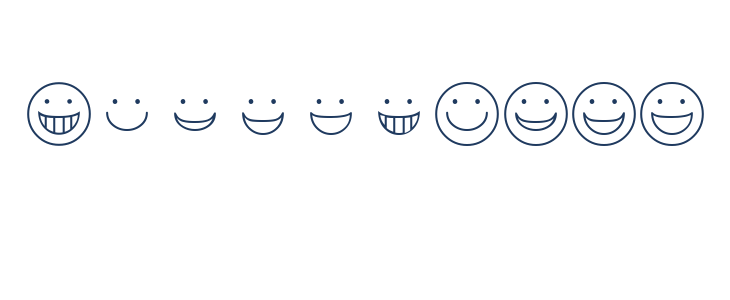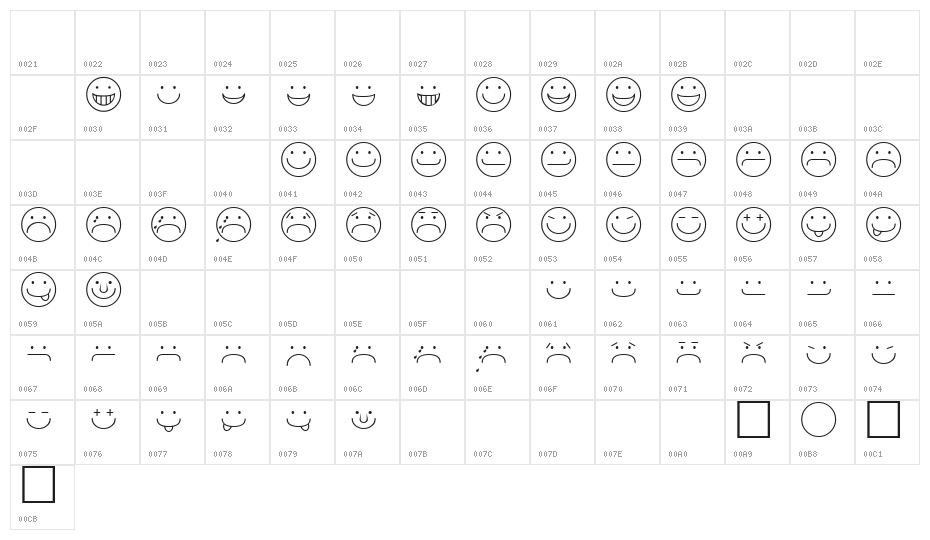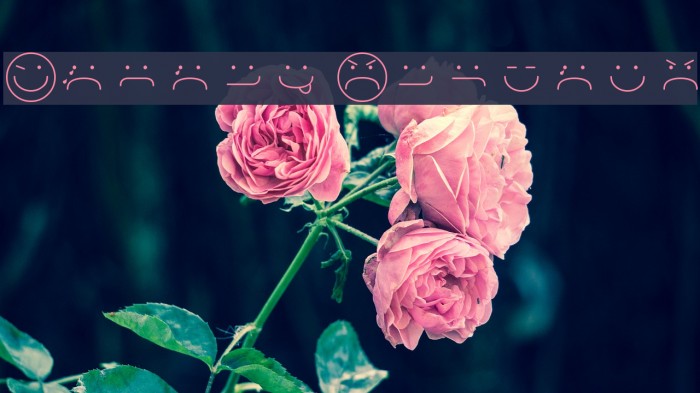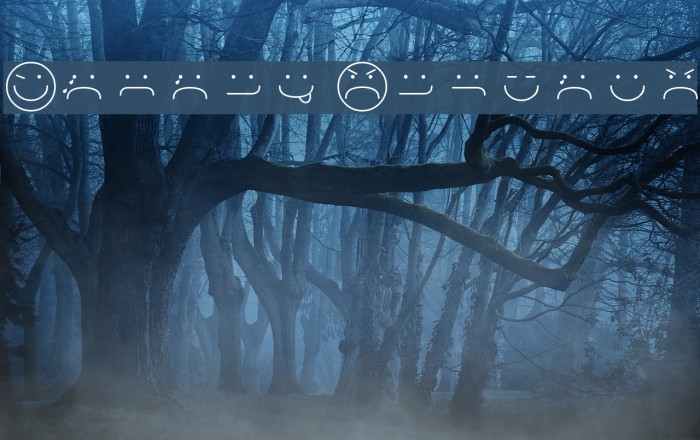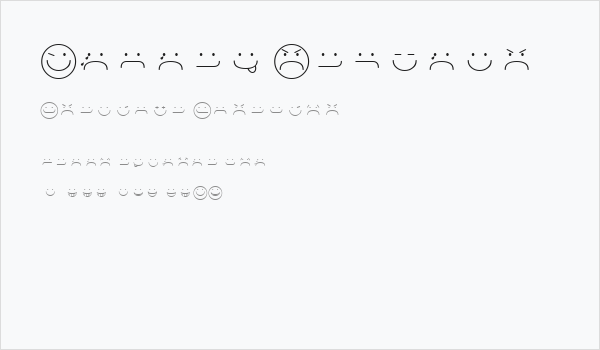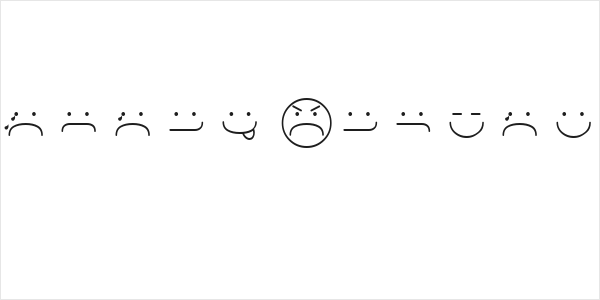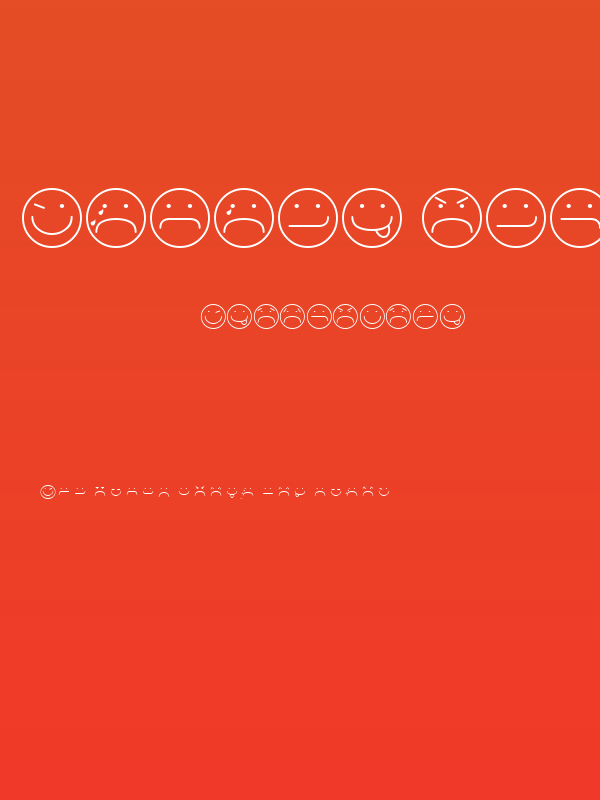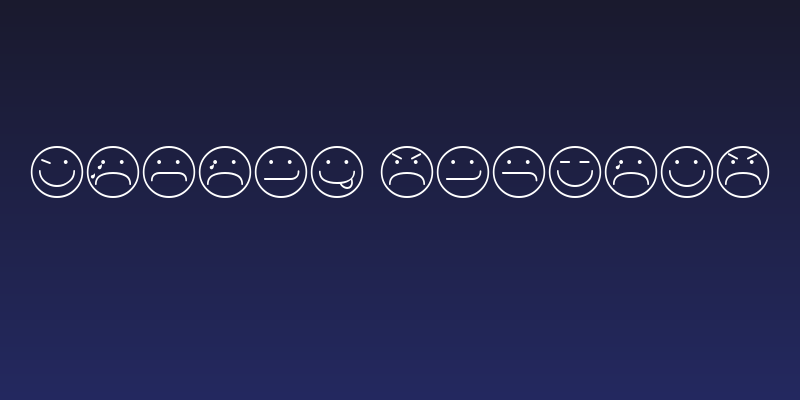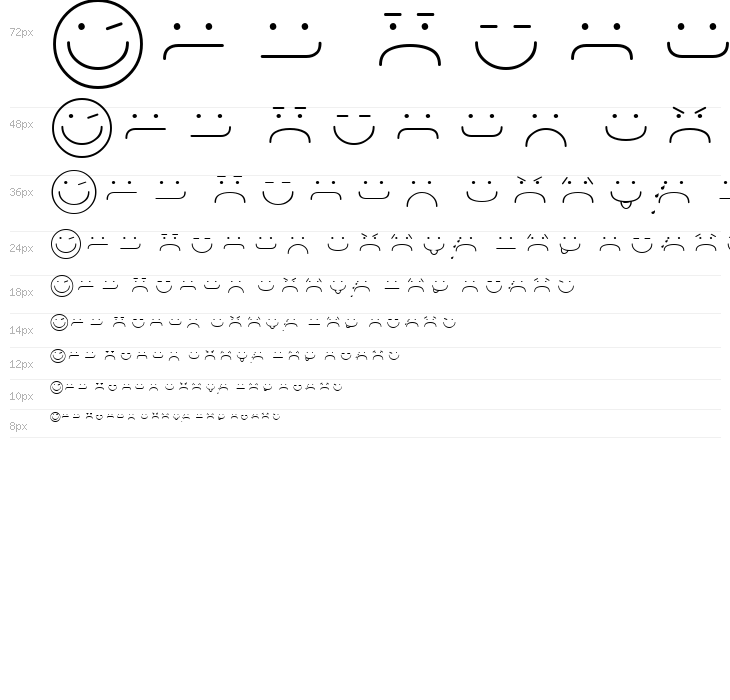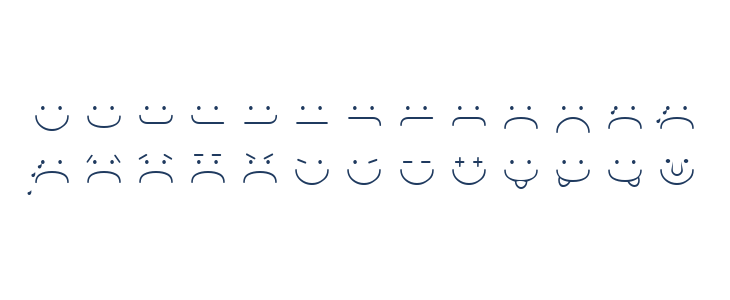
Smiley Regular Font
| Caz de utilizare | Icons, Decorative elements |
| Proiecte propuse | Ideal for use in children's books, playful branding, social media graphics, or any project requiring expressive icons. |